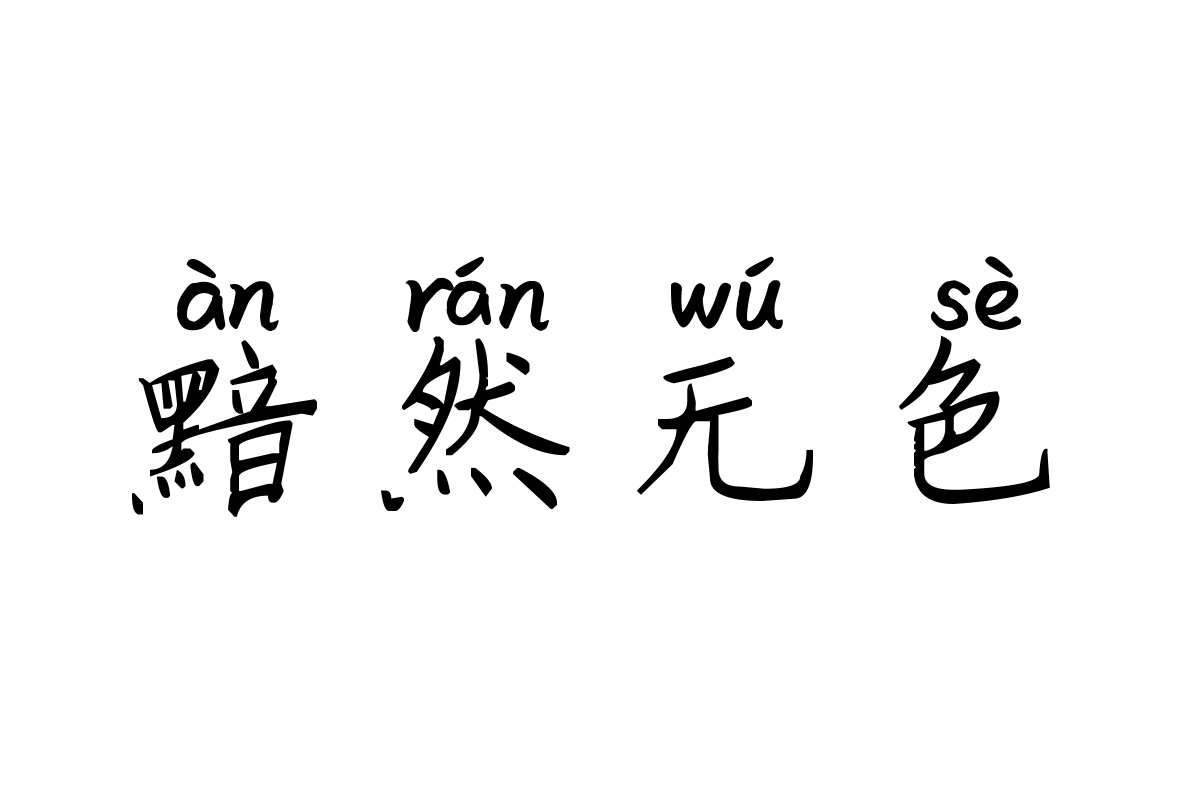
米开彩云追梦拼音体是一种字体,它的设计灵感来源于中国传统的书法艺术。这种字体的特点是笔画流畅,结构紧凑,既有楷书的规整,又有行书的灵动。
米开彩云追梦拼音体的字体特点如下:
1. 笔画流畅:这种字体的笔画线条流畅,没有太多的顿挫感,给人一种轻松愉悦的感觉。
2. 结构紧凑:虽然笔画流畅,但每个字的结构都是精心设计的,使得整个字体看起来紧凑有序。
3. 规整与灵动相结合:这种字体既有楷书的规整,又有行书的灵动,使得整个字体既有美感,又不失个性。
4. 易于识别:由于这种字体的设计独特,所以很容易让人记住,便于阅读和识别。
5. 适用范围广泛:这种字体适用于各种场合,无论是正式的文件,还是日常的笔记,都能展现出其独特的魅力。